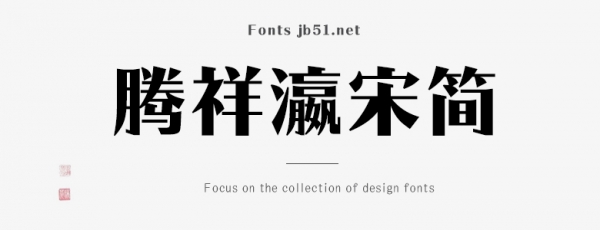
騰祥瀛宋簡(jiǎn)-W10是一款不錯(cuò)的藝術(shù)字體,由騰祥字庫(kù)出品,這款字體筆觸略顯粗實(shí),字形端正,適合應(yīng)用于藝術(shù)設(shè)計(jì)、平面宣傳設(shè)計(jì)、網(wǎng)頁(yè)設(shè)計(jì),書(shū)法字帖等領(lǐng)域,需要的朋友可以前來(lái)本站下載。
此款字為騰祥瀛宋系列字庫(kù),是騰祥公司自主精心設(shè)計(jì)開(kāi)發(fā)的精品正文字庫(kù)。一共10款粗細(xì),以期滿足用戶不同領(lǐng)域的用字需求。此款字為瀛宋W10,可用于正文、大標(biāo)題等。整個(gè)系列字庫(kù)風(fēng)格完全一致,不管是常用字或是非常用字,字字精美、結(jié)構(gòu)端正、重心平穩(wěn)、美觀實(shí)用。此款字為騰祥公司推送《2019森澤字體大賽》參賽作品。